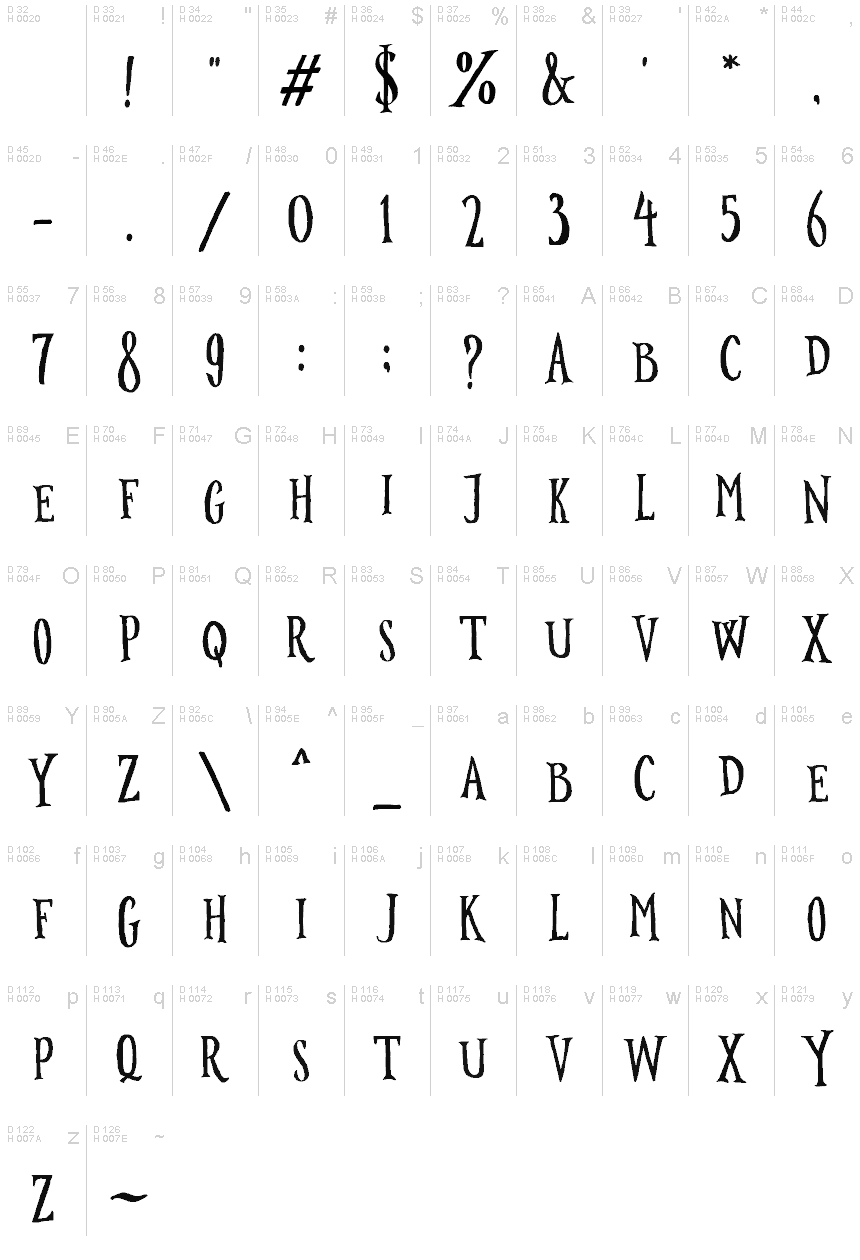
Surabanglus Normal
Surabanglus diambil dari judul salah satu cerita pendek Ahmad Tohari dalam bukunya "Senyum Karyamin". Surabanglus sendiri adalah nama dari sejenis ketela yang beracun jika dimakan.